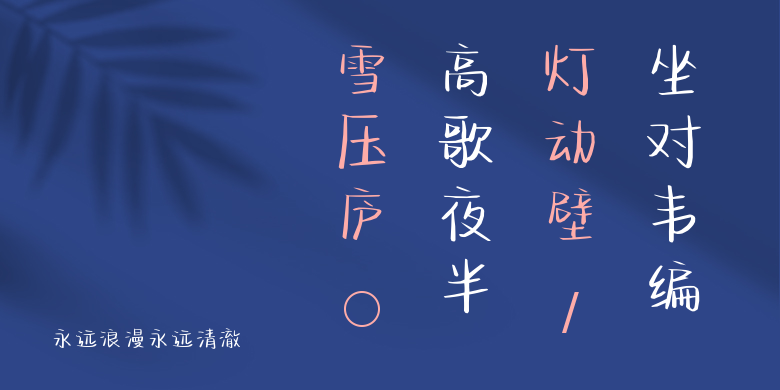
永远浪漫永远清澈
永远浪漫永远清澈,这款字体结构工整、笔画清晰,兼顾美观与易读性,适用于标题、正文、海报、包装、LOGO 等多种场景。字形优雅稳定,风格百搭耐看,适配日常排版与创意设计,让文字呈现更舒适、更具质感。永远浪漫永远清澈一笔一画,皆是细节,以均衡的比例、流畅的线条打造舒适视觉体验,字形端正大气,风格简约现代。无论是商业设计、品牌宣传还是日常排版,都能轻松驾驭,让文字更有格调与力量。永远浪漫永远清澈字体下载。